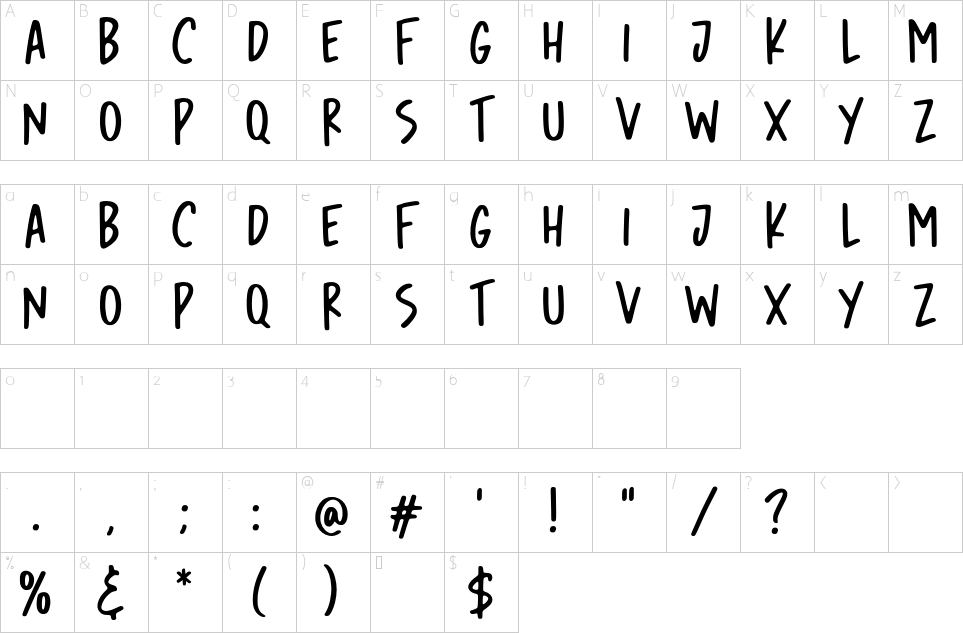
Avocado Cake Font – Download Grátis
Descubra a frescor e a criatividade da Avocado Cake Font em sua próxima projeto gráfico. Esta fonte foi criada pela Letteralle Studios e já foi baixada 2.970 vezes para Windows e Mac. Com um toque de frescor e sabor, a Avocado Cake não apenas enriquece a aparência de seus materiais, como também oferece uma textura única e vibrante. Esta fonte é perfeita para aqueles que buscam um toque de criatividade e colorido em seus projetos digitais. Não perca essa oportunidade de adicionar um pouco de diversão e beleza à sua arte digital. Descubra a Avocado Cake Font hoje.